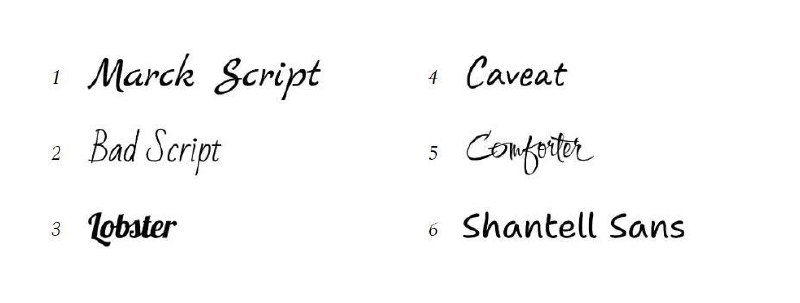
Седьмая часть сериала, в котором шрифтовые дизайнеры оценивают качество кириллицы в бесплатных шрифтах Гугла. Коротко выводы:
- Marck Script — шляпа
- Bad Script — хороший, но применять с осторожностью
- Lobster — качественный, но примелькавшийся шрифт
- Pacifico — качественно, но из-за технической реализации применять осторожно
- Caveat — норм, но языковая поддержка реализована неидеально
- Comforter — применять ограниченно и осторожно
- Shantell Sans — хороший